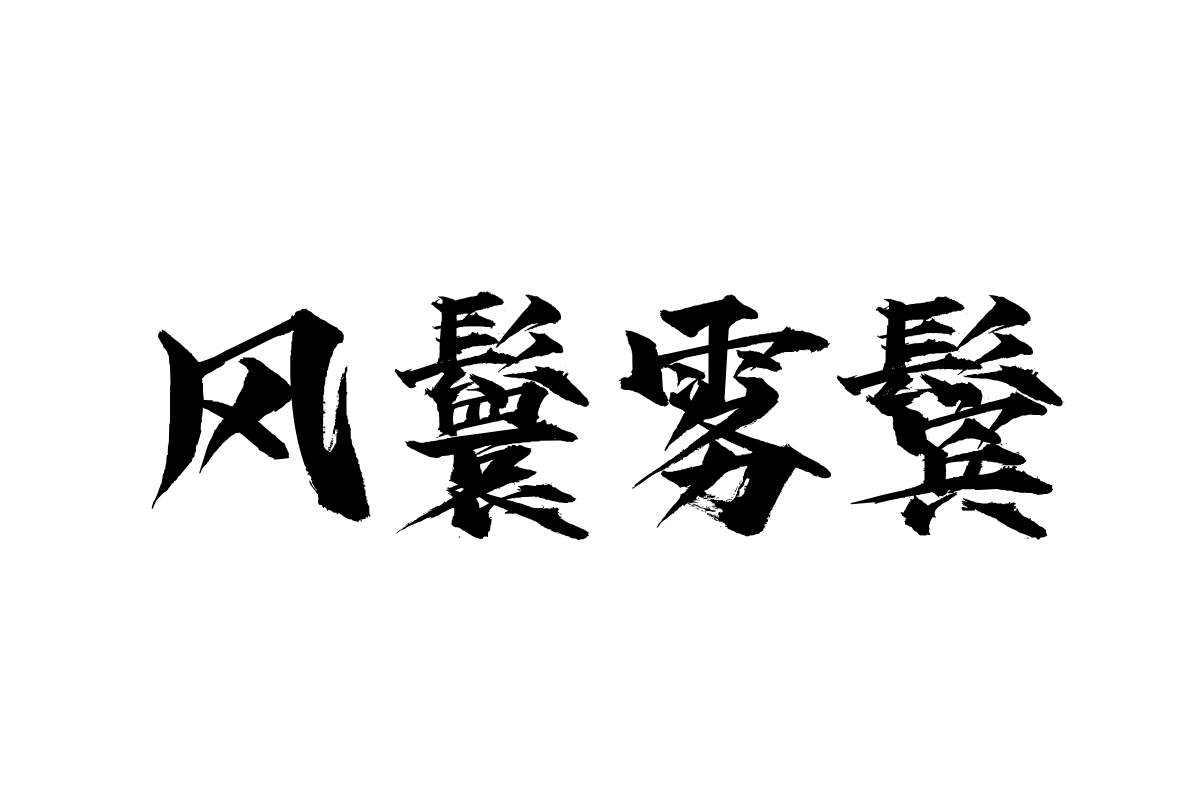
汉仪东海墨行是一款具有独特书法风格的中文字体,其笔画流畅自然,线条粗犷有力。该字体适用于各种设计场景,如广告、海报、书籍封面等。汉仪东海墨行的特点如下:
1. 字形饱满圆润,线条流畅自然,给人一种古朴典雅的感觉。
2. 笔触粗细适中,既有力道感又不失柔美,适合用于书写和打印。
3. 字体结构紧凑,笔画间隔均匀,易于阅读和识别。